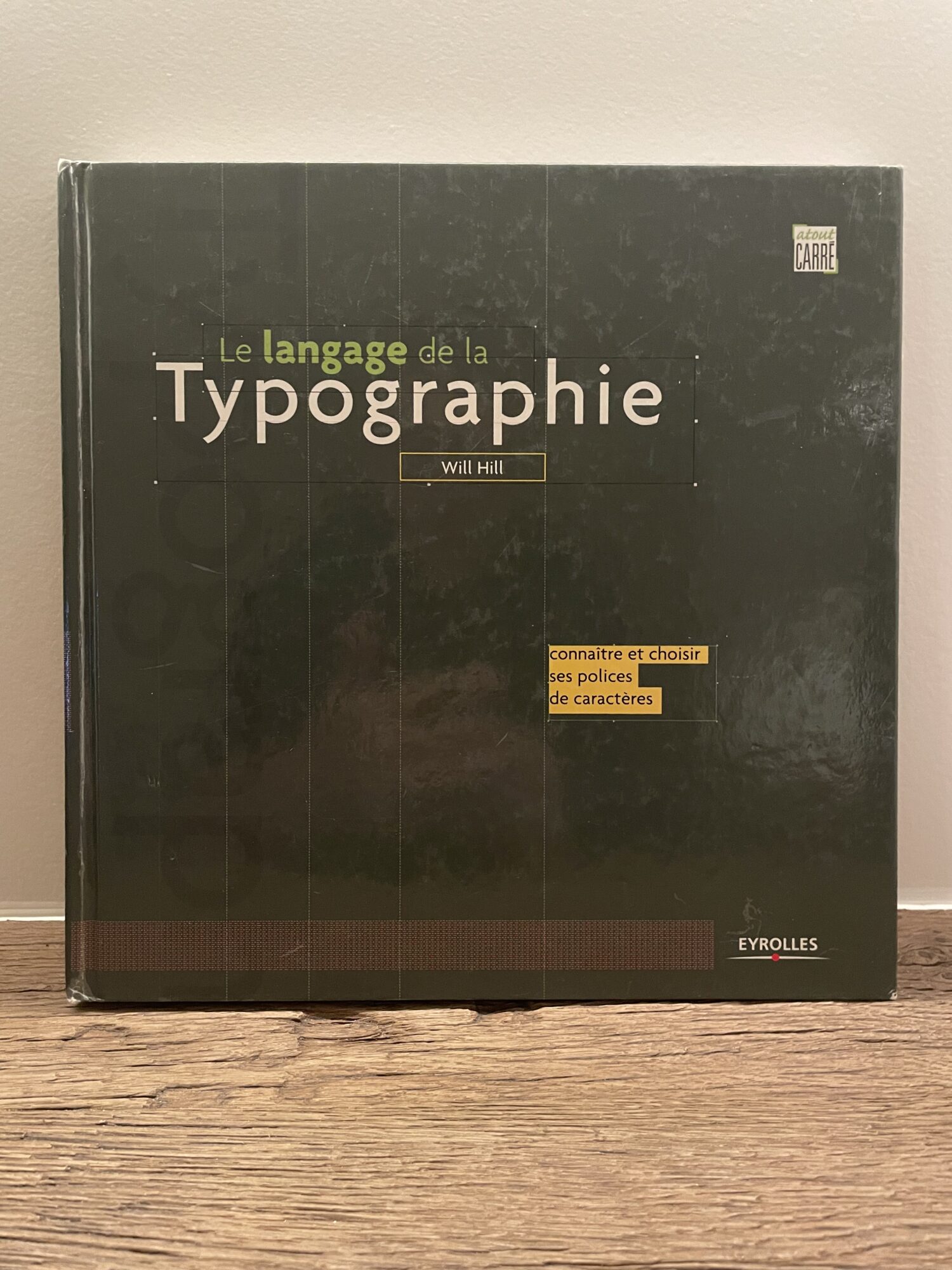
Le langage de la typographie
Hardcover: Connaître et choisir ses polices de caractères
Het eerste deel van dit boek beschrijft de ontwikkeling van de typografie door de eeuwen heen, vanaf de uitvinding van de losse letter door Gutenberg tot aan de digitale revolutie. U leert hoe letterfamilies (Humanen, Garaldes, Didones …) zijn ontstaan, beïnvloed door technologische vooruitgang en grote artistieke stromingen. Adviezen over de keuze van lettertypen en lay-out, evenals een overzicht van de professionele conventies, bieden de onmisbare basis voor elk kwalitatief hoogstaand werk.
Het tweede deel presenteert een selectie van lettertypen – klassiekers zoals Garamond, Bodoni, Helvetica, Univers … of meer fantasierijke zoals Scala Jewel of Pepperwood – ingedeeld in zestien categorieën en geïllustreerd met voorbeelden van drukwerk. Elk lettertype wordt uitvoerig besproken: de geschiedenis, de grafische kenmerken en de sterke punten. Dezelfde tekst, gezet in romein, cursief en vet voor elk lettertype, maakt het mogelijk om het ruimtegebruik en de visuele impact te beoordelen en te vergelijken.
Aan het einde van het boek vindt u talrijke tips voor het opbouwen van uw eigen typotheek, evenals een verklarende woordenlijst met vaktermen.